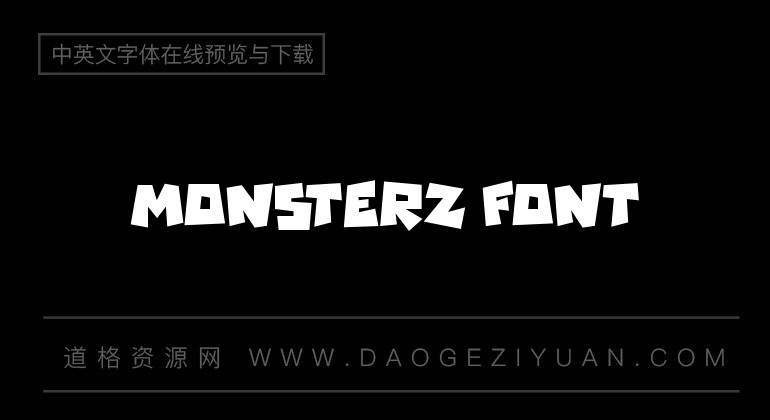
Monsterz Font 是一种具有吸引力的手写风格字体,其特点是充满了趣味性和个性化。该字体由 Pizzadude 设计并发布,可在 Pizzadude.dk 网站上免费下载。 Monsterz Font 包括大写字母、小写字母、数字和标点符号,每个字符都具有独特的设计。这种字体的主要特点是每个字符都有一种带有独特特征的卡通化风格。Monsterz Font 的设计还融合了不同的线条和曲线,使得字体具有非常生动的视觉效果。 Monsterz Font 适用于许多设计领域,例如海报、标志、网页设计等。它可以为您的设计项目增加趣味性和独特性。内容介绍
Monsterz Font是一款非常不错的手写艺术字体,具有很好的视觉感,适合于文化类的宣传设计、商业类品牌的广告和产品包装设计以及个性化文字排版等较多场景。